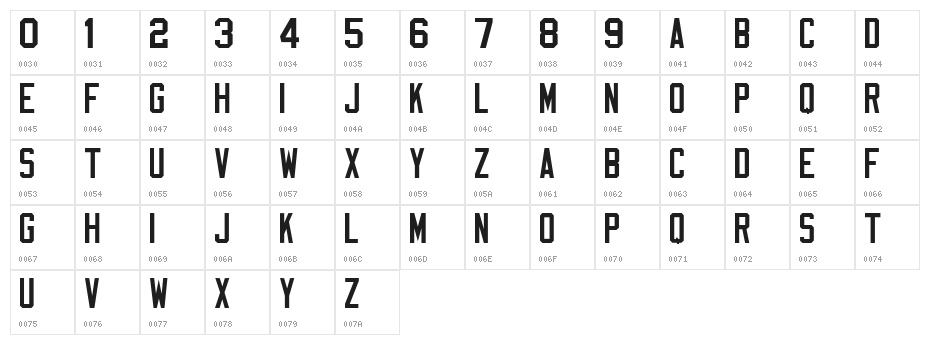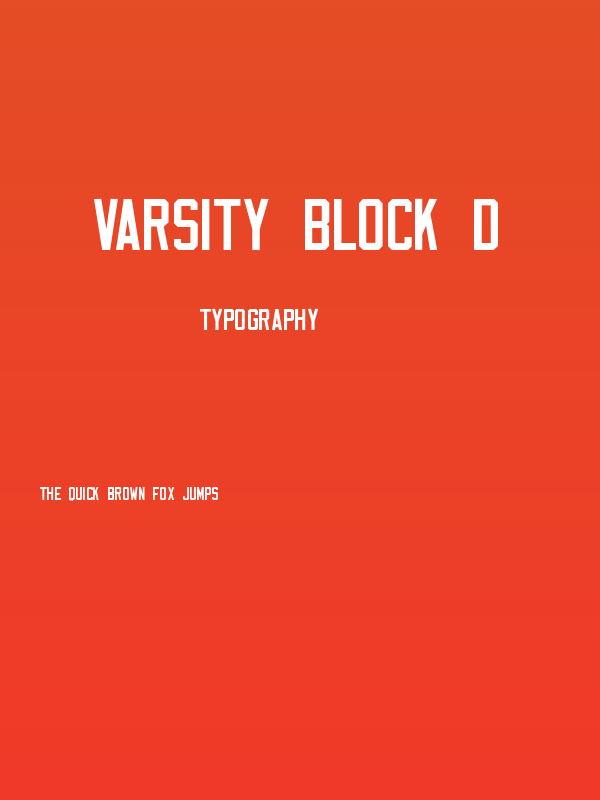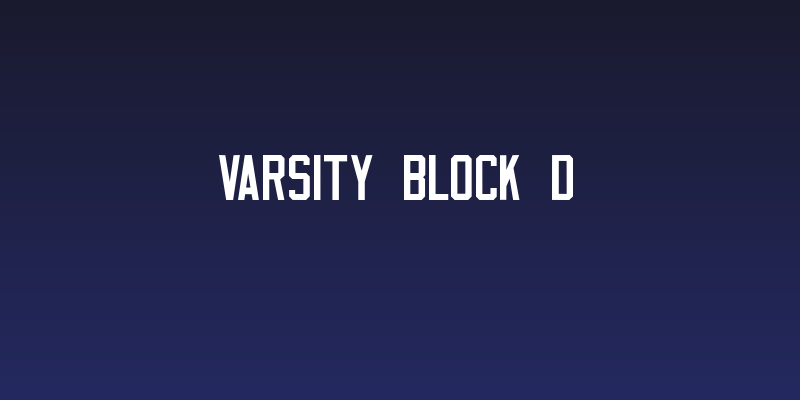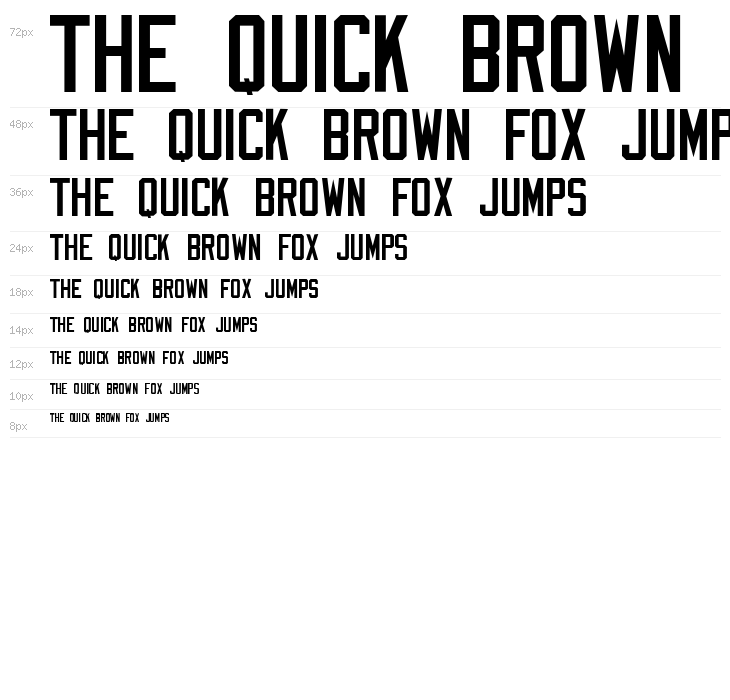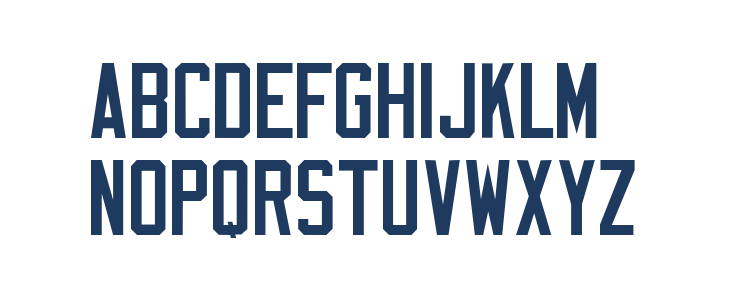
Varsity Block D Font
| Vorgeschlagene Projekte | Perfect for sports team branding, event posters, school merchandise, and any project needing a strong, collegiate aesthetic. |